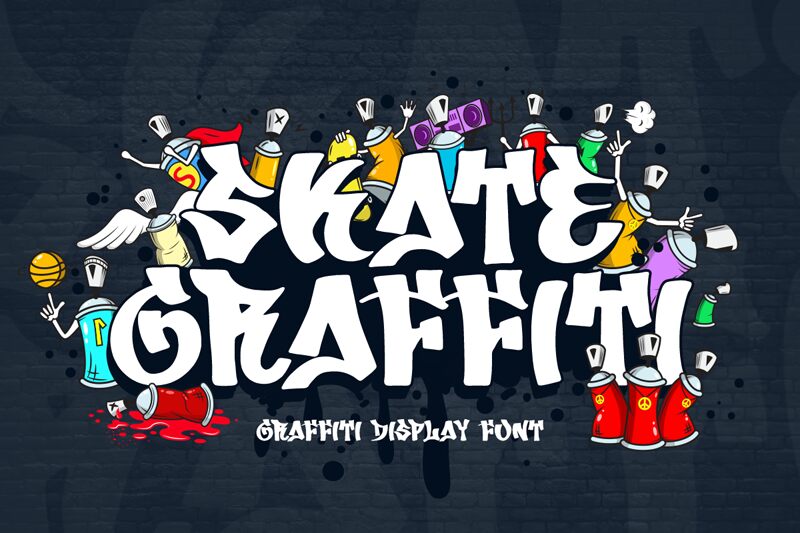
Skate Graffiti od Kong Font to darmowy font graffiti o ostrych, ręcznie ciosanych kształtach i surowym rytmie ulicznego tagu. Litery łączą twarde kąty, wygięte cięcia i nierówne krawędzie, dzięki czemu zestaw sprawia wrażenie ręcznie pisanych, a nie mechanicznie wygenerowanych znaków.
Skate Graffiti świetnie sprawdzi się w logo skateshopów, nagłówkach plakatów, ulotkach wydarzeń, okładkach albumów, naklejkach i grafikach ściennych. Nieregularne kontury i zwarta energia czynią go silnym wyborem wszędzie tam, gdzie potrzebny jest surowy, graffiti-akcent, który nie wygląda na przesadnie wygładzony.